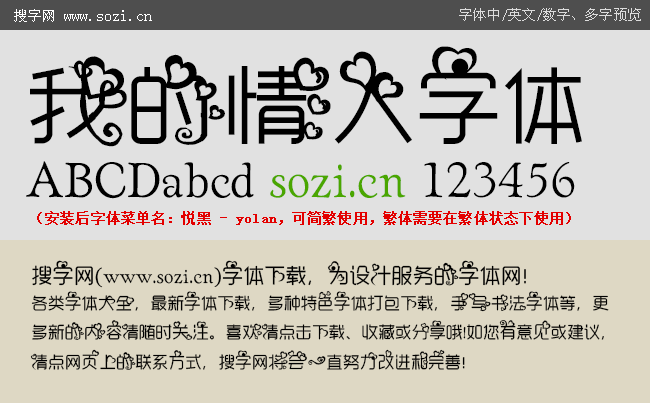
我的情人字體
搜字網(wǎng)給大家提供一款很有趣的手機(jī)中文字體下載。字體名字叫我的情人字體,這款手機(jī)字體是在造字工房悅黑體字體筆畫間插入了漂亮的卡通心形圖案。即保持了悅黑體易識(shí)別的風(fēng)格,又增強(qiáng)了趣味性,特別適合喜歡手機(jī)字體個(gè)性一些的朋友在手機(jī)上安裝使用。